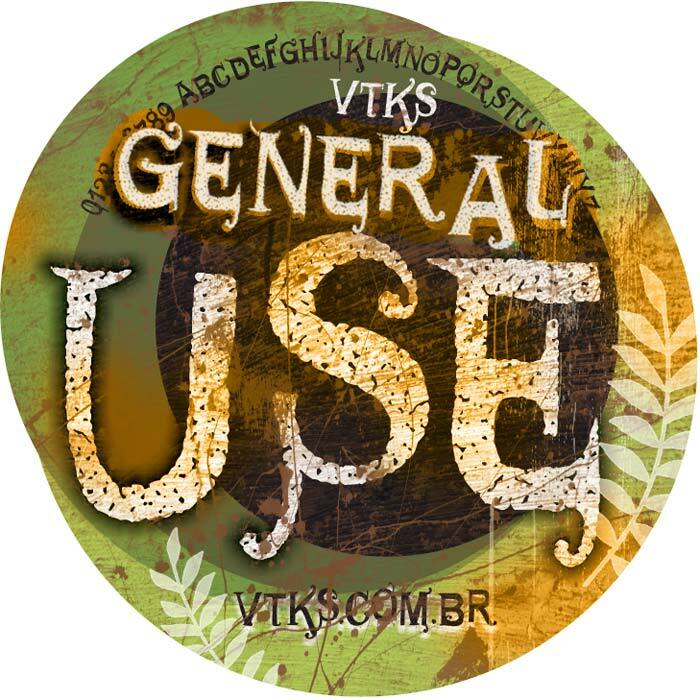
VTKS General Use, di Douglas Vitkauskas, è un carattere display gratuito, dal look usurato e arricciato, con un carattere ruvido e teatrale. Le sue maiuscole irregolari combinano forme serif consumate con tratti avvolgenti e riccioli decorativi improvvisi, creando una rivisitazione grintosa della grafica dei vecchi manifesti.
Questo carattere gratuito è perfetto per locandine di concerti, copertine di fanzine, grafiche di album, titoli horror e per il branding di locali alternativi. Funziona al meglio in titoli brevi o scritte di copertina, dove la texture erosa e le volute oversize hanno abbastanza spazio per definire l'atmosfera.